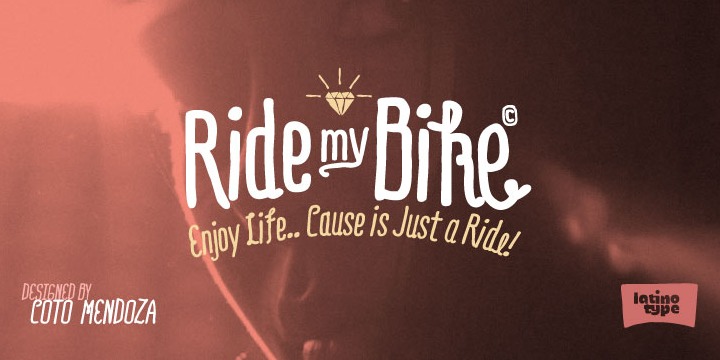
Schrift für Kinder-Schatzkarte gesucht...
Bold und Regular, sollte auch in 9 Pkt, gut lesbar sein.
Die Schatzkarte soll so anmuten, als hätte ein Kind im Alter von ca. 13/14 Jahren den Text geschrieben.
Sie sollte jedoch von Kindern zwischen 8 und 15 problemlos lesbar sein.
Hat das werte Forum einen Tipp für einen passen Font? Gerne auch ein gut laufender Freefont.
Hallo Och,
mein Favorit für solche Fälle ist die Tierra Nueva des geschätzten Forumskollegen Sebastian Nagel. :-)
Nachtrag:
Sorry, dass die Karte wie von Kinderhand geschrieben aussehen soll, ist mir beim ersten Lesen durchgerutscht!
Zum Glück hat R::bert besser aufgepasst.
Die Schatzkarte soll so anmuten, als hätte ein Kind im Alter von ca. 13/14 Jahren den Text geschrieben. Sie sollte jedoch von Kindern zwischen 8 und 15 problemlos lesbar sein.
Das kommt sicher auch etwas darauf an, wo Du den Schwerpunkt siehst. Kathrin hat einen Vorschlag gemacht, der auf eine wunderbare Schatzkartenoptik aus ist.
Willst Du dass es eher »kind- bzw. jugendlich« geschrieben aussieht, kannst Du Dir ja mal die hier ansehen:
· Comic Jens
· Sweetie Pie
· Homework
· Five Cents
· Apple Casual*
· AlphaMack
Folgende digitalisierte Handschriften liegen vielleicht irgendwo dazwischen:
· Luna
· Rabiohead
· Miss Brooks
· Margarosa
· Joe Hand
*Außer dieser dürfte der Rest, soweit ich das im Moment überblicken kann, Freefont-Material sein ; )
Ride my bike fänd’ ich für den Kontext recht lässig.
Vorteile:
· Einige Schriftschnitte und passende Dingbats im Angebot
· Außerdem sind viele Ligaturen enthalten, welche für einen authentischer wirkenden, handschriftlichen Eindruck sorgen
· Des Weiteren gibt es Alternativen (einfaches a und g) zur besseren »Zielgruppenansprache« ; )
»Ride my Bike« ist cool, mir aber für die Textmenge zu unruhig. ich habe die Comic Jens genommen, die ist recht deutlich und irgendwie unaufgeregt.